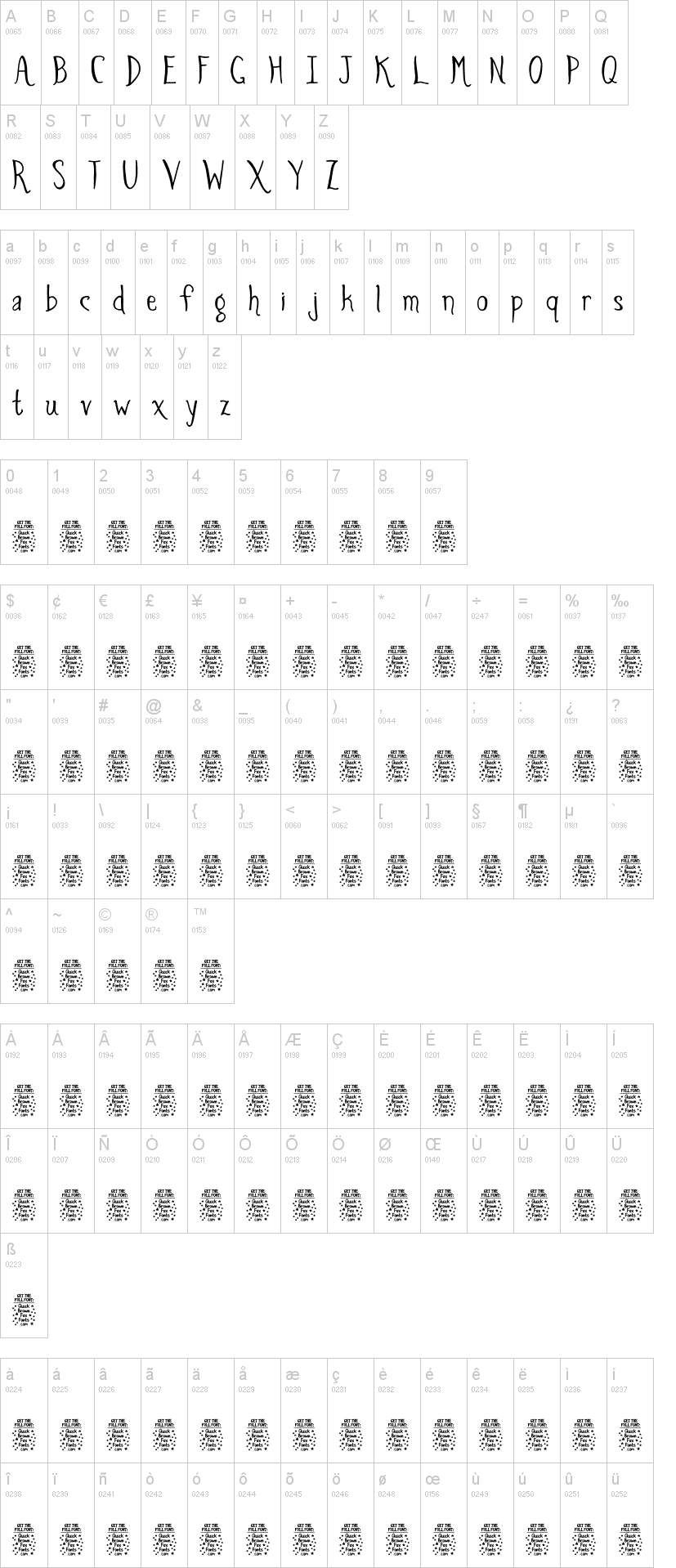
Spiders and Sparrows 是一种由美国设计师 Ethan Dunham 创建的免费字体。该字体于2011年发布,目的是为了提供一种具有良好可读性的手写风格字体。 Spiders and Sparrows 字体包括两种不同的风格:一种手写体,另一种是粗体。它的字母形状略微扭曲,但仍保持了良好的可读性。该字体的设计风格充满了轻松、随意的感觉,适合在印刷品、广告、海报等各种设计作品中使用。 此外,该字体还包括了一些其他的特殊字符和标点符号,例如箭头、星号、括号等,可以满足使用者各种不同的需求。内容介绍
Spiders and Sparrows是一款非常不错的手写艺术字体,具有很好的视觉感,适合于文化类的宣传设计、商业类品牌的广告和产品包装设计以及个性化文字排版等较多场景。